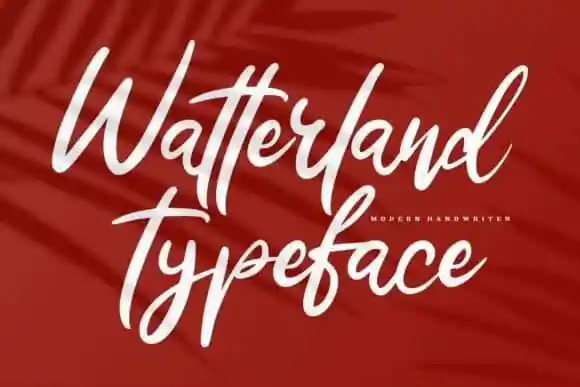
Watterland Script Font – Download Grátis
A Watterland Script Font é uma criação surpreendente que resulta de uma harmoniosa combinação entre uma caneta a pincel e uma lapiseira. Essa fonte transmite um encanto autêntico com suas linhas delicadas e elegantes, criando designs memoráveis. Desenvolvida por Vunira Design, Watterland é uma tipografia moderna e sofisticada que abrange uma variedade impressionante de usos. Seja em cartazes, websites ou design gráfico, esta fonte irá elevar qualquer projeto para um patamar superior. Não perca a oportunidade de trazer uma personalidade única e autêntica aos seus designs com Watterland Script Font.